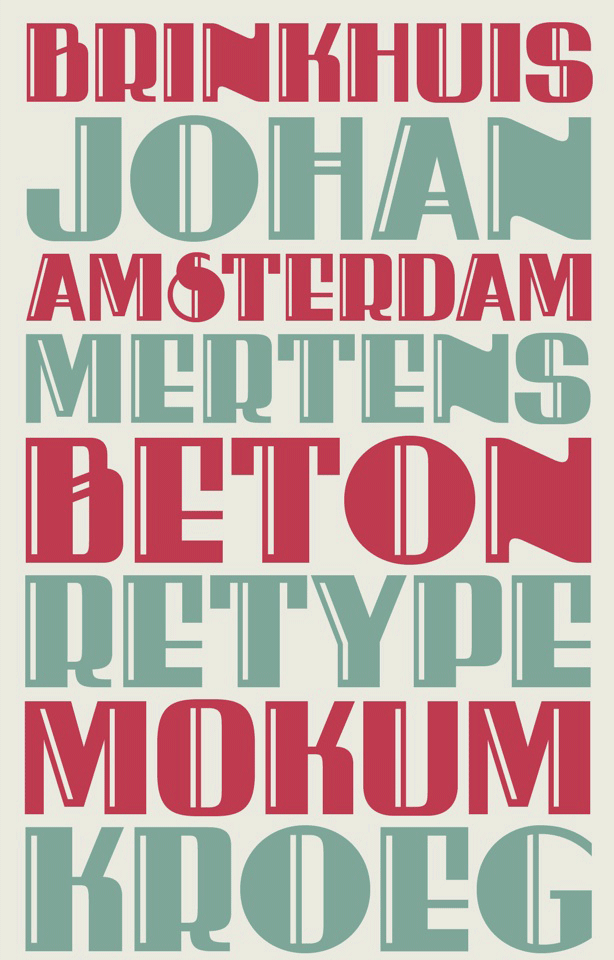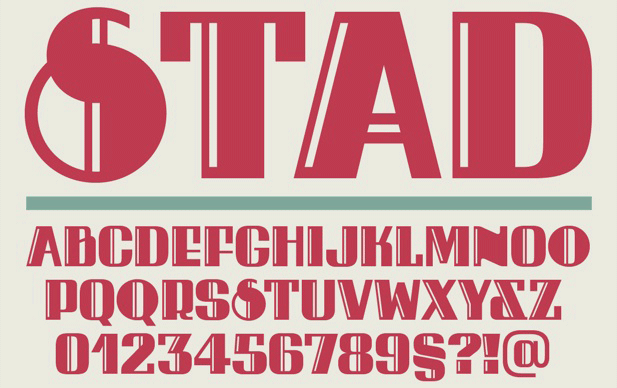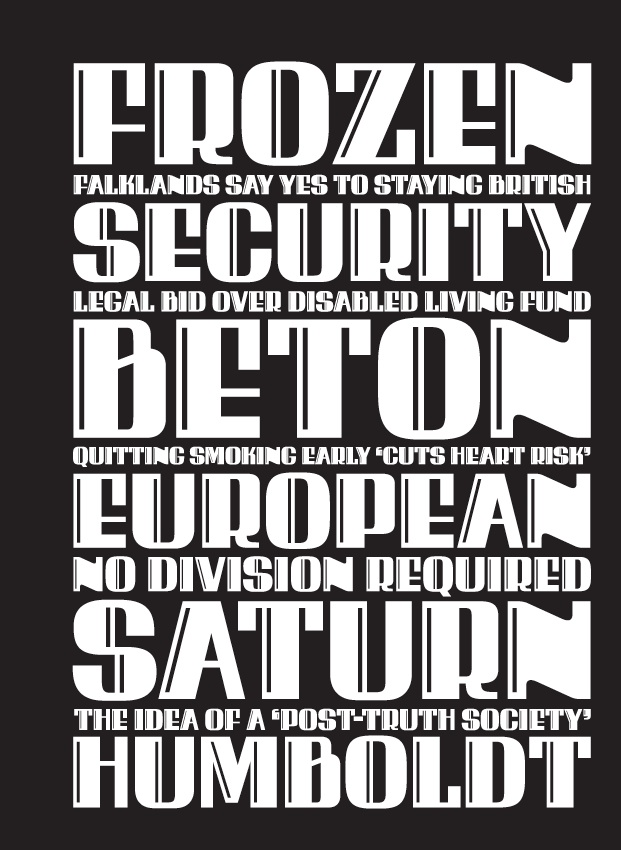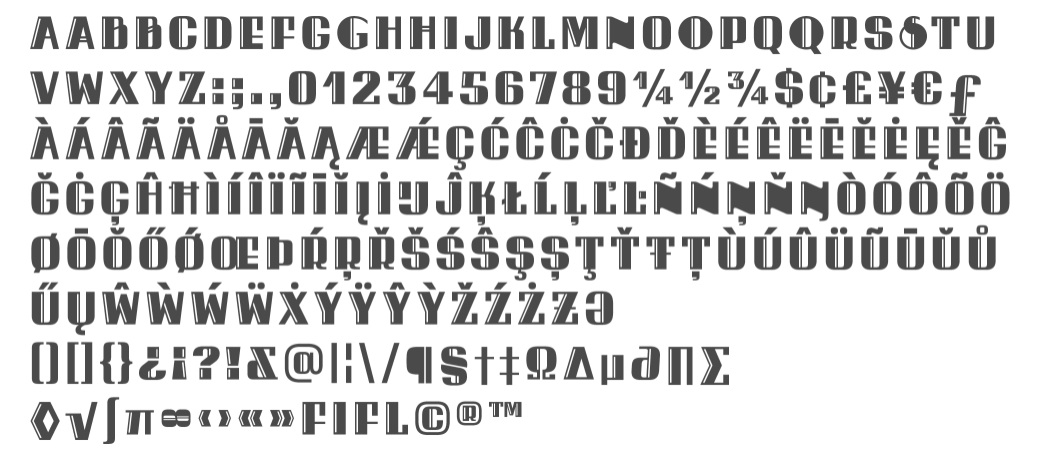
Art Deco typografisch interpretiert
Eine neue Schrift der ReType Foundry spielt mit Beschriftungen aus der Zeit des Art Deco.
Als eine freie Interpretation der Art Deko Buchstaben, die sich auf diversen Häuserfassaden im Viertel Watergraafsmeer in Amsterdam befinden, beschreibt ReType Gründer Ramiro Espinoza die Schrift Brinkhuis. Während die Letterings vermutlich von dem Architekten Dick Greinet stammen, kommen die Lettern der Brinkhuis ganz sicher von Paula Mastrangelo. Die aus Argentinien stammende und in Barcelona lebende Typedesignerin beseitigte verschiedene Ungereimtheiten der Vorlage, fügte Buchstaben und Satzzeichen hinzu und machte so aus einem simplen Alphabet eine bemerkenswerte Versalschrift für aufmerksamkeitsstarke Poster, Buchcover oder Logos.